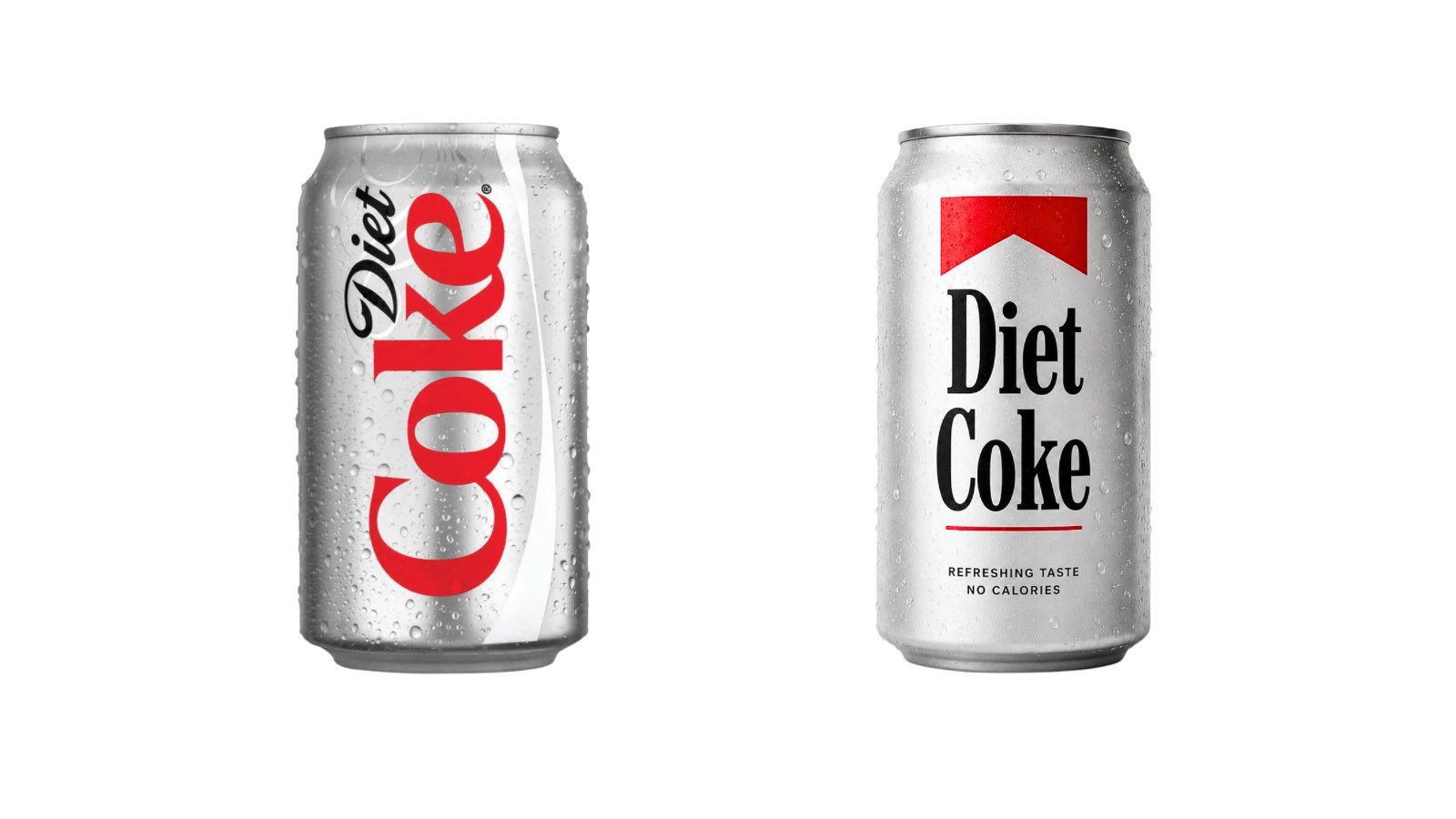
Todos sienten lo mismo sobre la nueva tipografía de Coca-Cola
Ayer nosotros traer Tienes la noticia de que Coca-Cola ha presentado un nuevo logo de marca; JKR se ha sometido a una revisión integral del diseño centrándose en la tipografía. Esto incluye un uso más destacado de la fuente “Better With” creada para la marca. asociados brody 2023. El tipo de letra se diseñó originalmente para campañas festivas y ahora es fundamental para el marketing y el empaque de la marca.
Pero los fanáticos rápidamente descubrieron similitudes inesperadas. La fuente serif, algo retro, se compara con la de los cigarrillos Marlboro. Si bien la fuente es diferente, la similitud es innegable, y muchos usuarios de redes sociales han señalado la ironía de una marca de bebida azucarada que aparentemente se inspira en el diseño de uno de los productos adictivos más famosos del mundo.